光明日报北京9月23日电(记者 李韵)22日,“字美中华——中华精品字库工程公益应用计划”在京启动。北京北大方正电子有限公司(以下简称“方正电子”)宣布,从即日起免费向公益组织、新闻出版单位、政府机构、学校、个人等提供“中华精品字库”首批15款字体的5年使用授权。
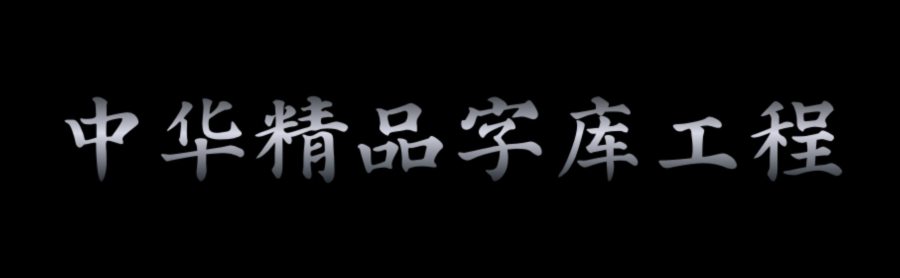
“中华精品字库工程”是方正电子于2017年申请立项并得到批准的。作为中华优秀传统文化传承发展工程支持项目,“中华精品字库工程”由中国文学艺术界联合会、国家语言文字工作委员会共同指导,将精选100位中国历代书法名家的代表作品,开发成计算机字库。中国书法家协会负责字体的遴选和质量审核,方正电子负责字库的开发工作。
2019年8月,作为迎接新中国成立70周年的重要展览,“字美中华——中华精品字库工程成果展”在国家博物馆展出,引起社会关注,让人们第一次感受到那些在历史长河中耀眼生辉的传世书法经典,如何在科技的转化下“走出”博物馆库房,走进今人生活。
“中华精品字库工程公益应用计划”就是要大力倡导并鼓励全民使用中华精品字库,让书法经典“走进”日常生活,全面“用起来”。方正电子董事长、总裁邵行特别提到,个人也可以在电脑上非商业使用。
中国书法家协会分党组副书记、秘书长郑晓华表示:“只有这些书法名家的字体在社会上广泛使用,才能让普通民众了解什么是美的书法。”他希望“通过中华精品字库的推广和应用,可以正本清源,活化应用,同步传递汉字的书法美、艺术美”。
在启动仪式上,方正电子字体设计总监仇寅介绍了目前推出的15款名家字体:颜真卿楷书、柳公权楷书、苏轼行书、黄庭坚行书、赵佶瘦金书、赵孟頫行书、赵孟頫楷书、文徵明行草、王铎行草、璺宝子碑楷书、鲁迅行书、沈尹默行书、舒同行书、启功行楷、刘炳森隶书。